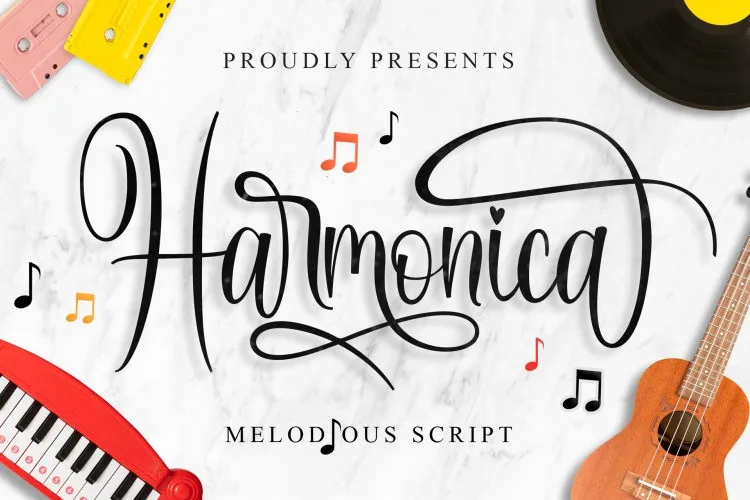
Harmonica Calligraphy Font – Fonte Grátis
Harmonica Calligraphy Font
Descubra Harmonica Calligraphy Font, uma elegante solución para los diseñadores que buscan una caligrafía moderna y natural en su próximo proyecto de diseño. Esta fuente de escritura script es un homenaje a la actual estética de la caligrafía de mano. Es perfecta para incrementar el nivel creativo de proyectos como logotipos, ilustraciones, camisetas, merchandising, ropa, revistas y muchos otros tipos de diseños. Con su estilo fluido y sinuosidad natural, esta fuente es una forma de amar la caligrafía moderna. Probéla y descubra por sí mismo los beneficios que brinda para sus proyectos gráficos. Harmonica Calligraphy es la solución perfecta para dar un nuevo enfoque a tus creativos proyectos con diseños únicos y distintos.